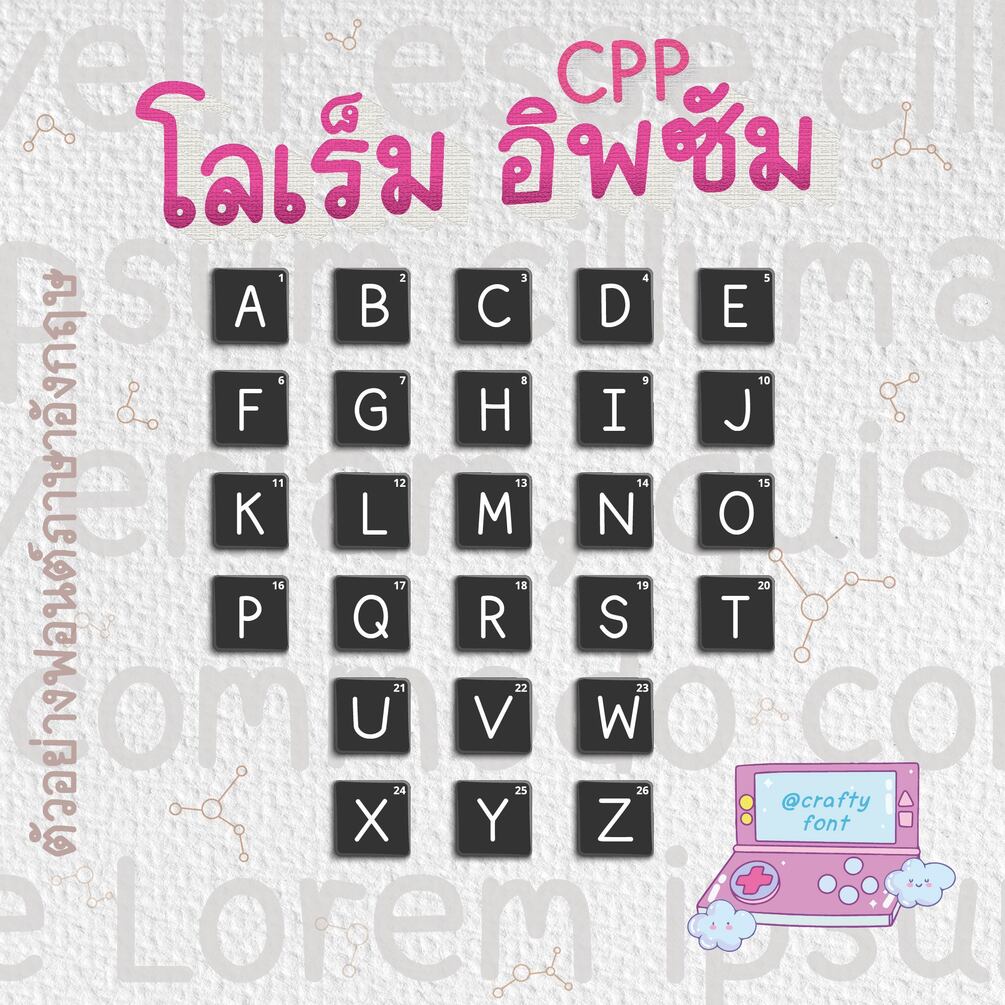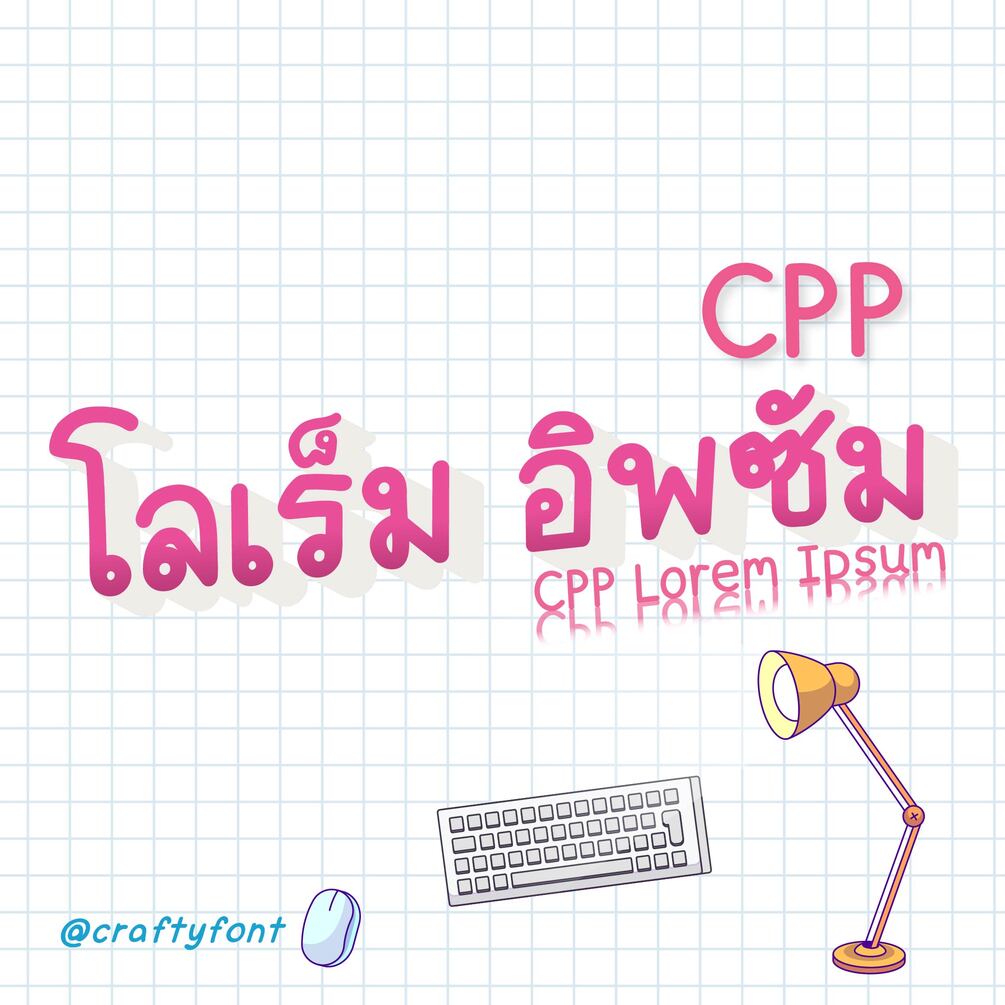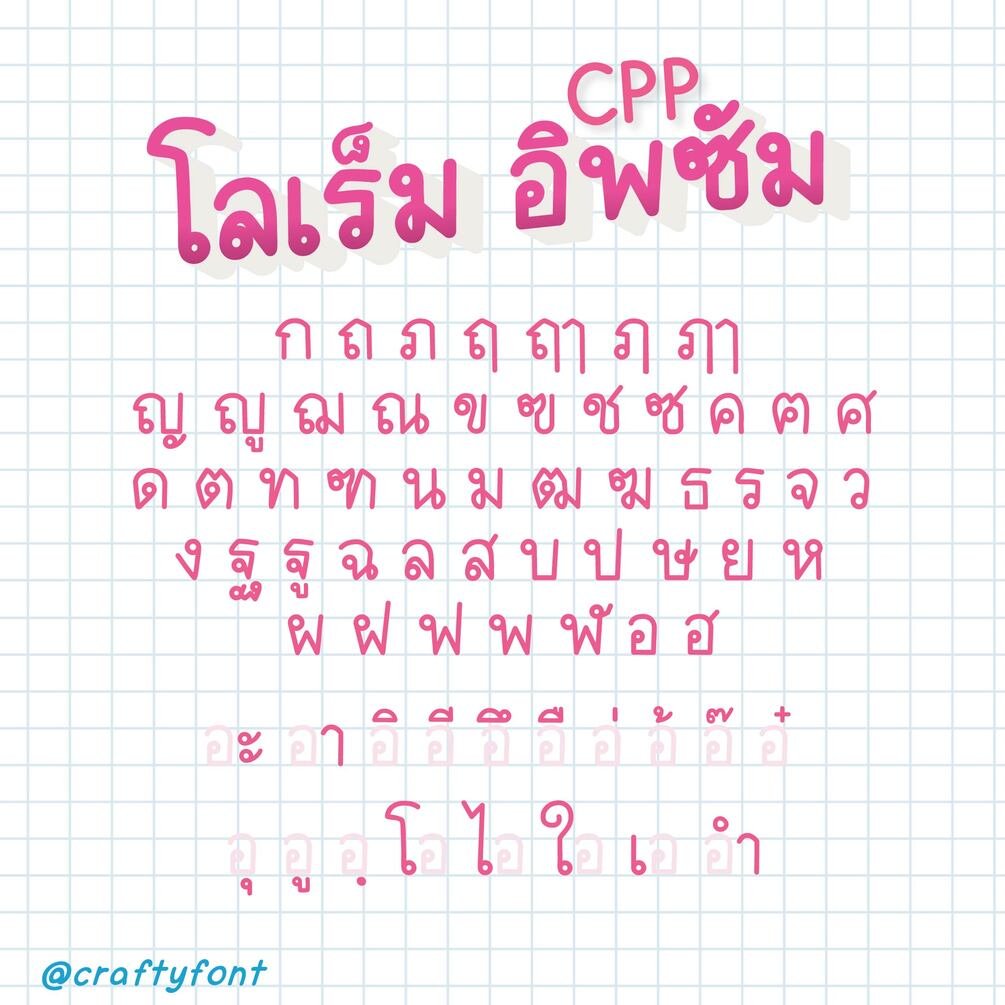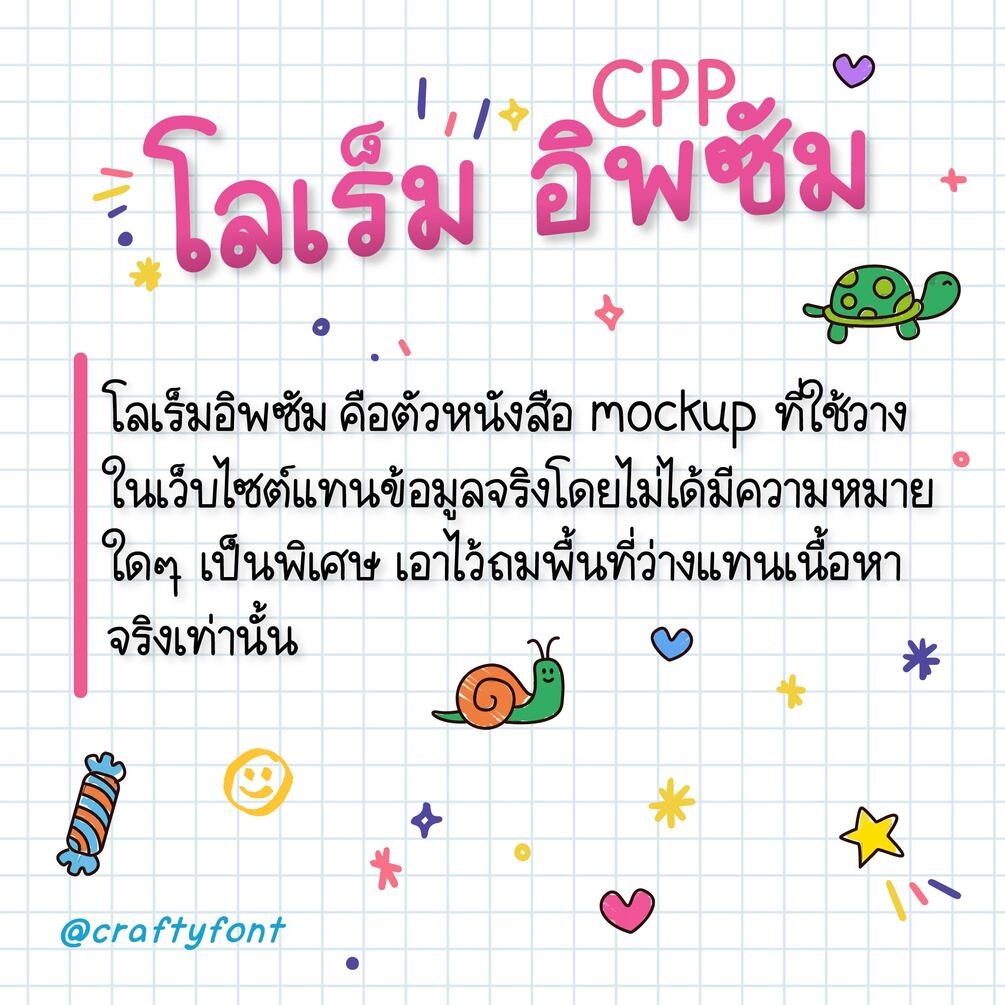
CPP lorem ipsum Font (ฟอนต์ซีพีพี โลเร็มอิพซัม)
โลเร็มอิพซัม (lorem ipsum) ตัว mockup อักษรเพื่อเป็นต้นแบบงานออกแบบที่ไม่มีความหมายอะไรทั้งนั้น แต่เอามาวางแล้วเท่ ประหนึ่งมีความหมาย! ❤️
(จริงไม่มีอะไร คิดชื่อไม่ออก  เลยเอาโลเร็มมาใช้แทนชื่อเลยละกัน -_-! แหะๆ)
ฟอนต์โลเร็มอิพซัมมีทั้งภาษาไทยและภาษาอังกฤษเลยนะคะ แฟมิลี่เซ็ตนี้มี 6 ขนาดด้วยกัน ทั้งตัวหนา ตัวบาง ตัวปกติ และตัวเอนของแต่ละขนาด สัญลักษณ์บวกลบคูณหารมีให้ใช้ครบ ฝากไว้ในอ้อมอกอ้อมใจพี่จ๋าด้วยนะจ๊ะ